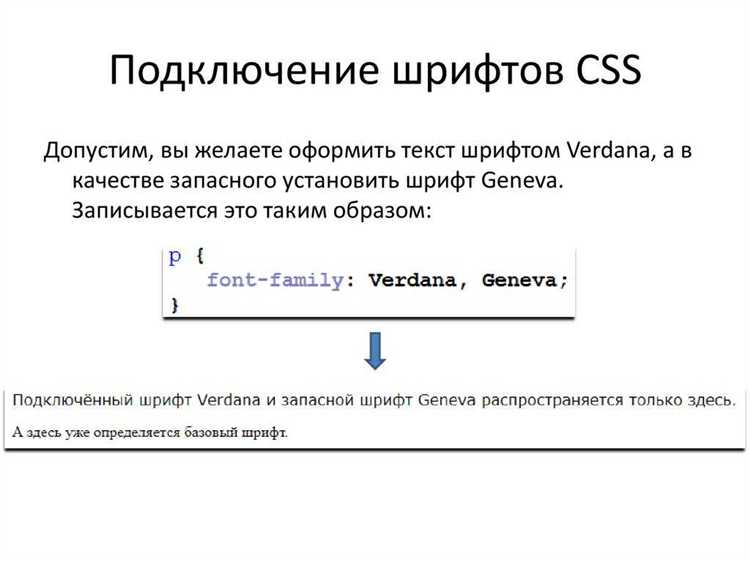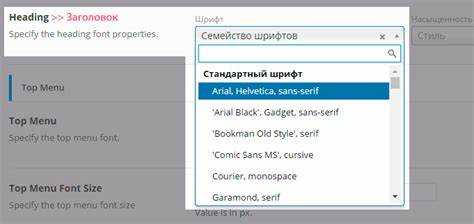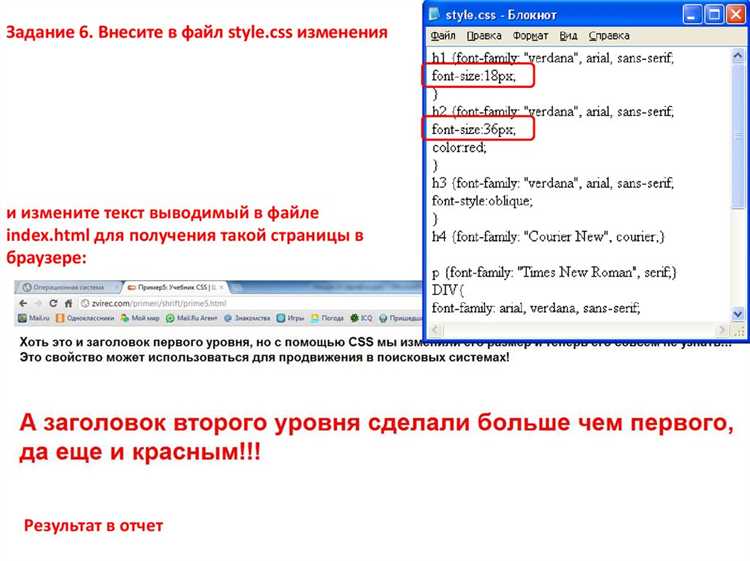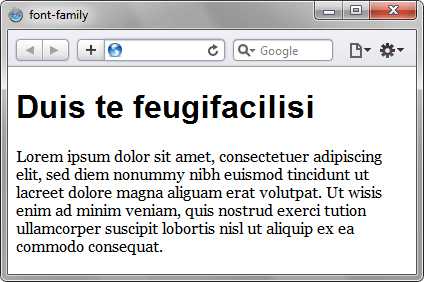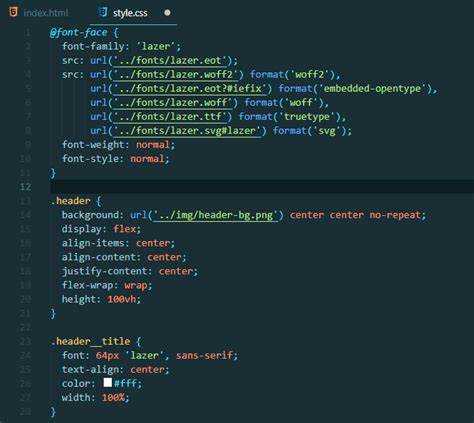
Шрифты без засечек – оптимальный выбор для экранов: они обеспечивают высокую читаемость и современный визуальный стиль. В CSS такие шрифты задаются с помощью свойства font-family, в котором указывается конкретное название гарнитуры или один из системных шрифтов, например Arial, Verdana или универсальное значение sans-serif.
Чтобы исключить зависимости от локальных установок пользователя, целесообразно использовать шрифты через @font-face или подключение через CDN, например Google Fonts. Пример: @import url('https://fonts.googleapis.com/css2?family=Inter&display=swap');
. Далее достаточно прописать font-family: 'Inter', sans-serif;
в нужном селекторе.
Универсальный стек шрифтов без засечек может выглядеть так: font-family: 'Segoe UI', 'Roboto', 'Helvetica Neue', Arial, sans-serif;
. Такой подход обеспечивает корректное отображение текста на различных платформах и устройствах, даже при недоступности конкретных гарнитур.
Для интерфейсных элементов предпочтительнее использовать гарнитуры с равномерной толщиной штрихов и хорошей адаптацией к малым размерам – например, Roboto, Inter или Helvetica Neue. Эти шрифты обладают высокой читаемостью и доступны в множестве начертаний, что важно для типографической иерархии.
Как указать шрифт без засечек с помощью свойства font-family
Чтобы задать шрифт без засечек, используйте свойство font-family со значением, включающим конкретное название шрифта и универсальное семейство sans-serif в качестве запасного варианта.
Например, для применения шрифта Arial, который относится к семейству без засечек, следует указать:
font-family: Arial, sans-serif;
Если приоритетный шрифт недоступен, браузер автоматически применит ближайший доступный шрифт из семейства sans-serif.
Рекомендуется указывать не менее двух альтернативных шрифтов, чтобы обеспечить кроссбраузерную совместимость. Например:
font-family: "Helvetica Neue", Helvetica, Arial, sans-serif;
Кавычки необходимы, если имя шрифта состоит из нескольких слов. Порядок имеет значение: сначала указывается предпочтительный шрифт, затем резервные.
При использовании сторонних шрифтов, таких как Google Fonts, подключение производится через @import
или <link>
, а затем шрифт указывается в font-family так же, с добавлением sans-serif в конце:
font-family: "Roboto", sans-serif;
Какие системные шрифты без засечек доступны в разных операционных системах
При выборе шрифта без засечек важно учитывать наличие системных гарнитур, установленных по умолчанию в различных ОС. Это гарантирует корректное отображение текста без необходимости подключения сторонних веб-шрифтов.
- Windows: наиболее универсальные sans-serif шрифты – Segoe UI (начиная с Windows Vista), Arial и Calibri. Segoe UI активно используется в интерфейсах системы. Calibri – основной шрифт Microsoft Office до версии 2021. Arial – совместим с большинством программ.
- macOS: системным стандартом является San Francisco (используется с macOS 10.11). Ранее активно применялись Lucida Grande и Helvetica Neue. Arial также доступен и совместим с Windows-средой.
- Linux: дистрибутивы, основанные на GNOME, обычно включают Ubuntu или Cantarell. В KDE-среде часто используется Noto Sans или Oxygen. Для совместимости рекомендуется также установка DejaVu Sans.
- Android: с версии 5.0 используется Roboto в качестве основного системного шрифта. В старых версиях применялся Droid Sans. Roboto поддерживает широкий набор символов и подходит для адаптивных интерфейсов.
- iOS: аналогично macOS – системным шрифтом является San Francisco. Он оптимизирован для Retina-дисплеев и адаптивного интерфейса.
Для кроссплатформенной верстки рекомендуется указывать стек системных шрифтов с fallback-поддержкой. Например: font-family: -apple-system, BlinkMacSystemFont, "Segoe UI", Roboto, Oxygen, Ubuntu, Cantarell, "Helvetica Neue", sans-serif;
Как подключить сторонний шрифт без засечек через @font-face
Для подключения стороннего шрифта без засечек через @font-face
, необходимо загрузить шрифт в формате WOFF или WOFF2 и указать путь к файлу в CSS. Ниже – пошаговая инструкция.
- Скачайте шрифт без засечек в формате
.woff
или.woff2
. Примеры: Open Sans, Roboto, Montserrat. - Сохраните файлы шрифта в директории проекта, например:
/fonts/
. - В CSS-файле добавьте объявление
@font-face
с точными параметрами:
@font-face {
font-family: 'Montserrat';
src: url('/fonts/Montserrat-Regular.woff2') format('woff2'),
url('/fonts/Montserrat-Regular.woff') format('woff');
font-weight: 400;
font-style: normal;
font-display: swap;
}
font-family
: задаёт имя, которое используется далее в стилях.src
: указывает путь и формат файла. Используйте оба формата для совместимости.font-weight
иfont-style
: соответствуют конкретному файлу шрифта. Указывайте отдельно для bold, italic и других вариаций.font-display: swap
: ускоряет загрузку, показывая текст системным шрифтом до загрузки основного.
Если вы хотите быть уверены, что шрифт не будет содержать засечек, можно указать в CSS конкретное семейство шрифтов, например, `font-family: Helvetica, Arial, sans-serif;`. Если вы указали только `sans-serif`, браузер выберет любой шрифт без засечек, доступный на устройстве пользователя, но это может привести к использованию разных шрифтов в зависимости от операционной системы и браузера. Указание конкретного шрифта в качестве первого элемента в списке гарантирует, что будет выбран именно тот шрифт, который вам нужен.